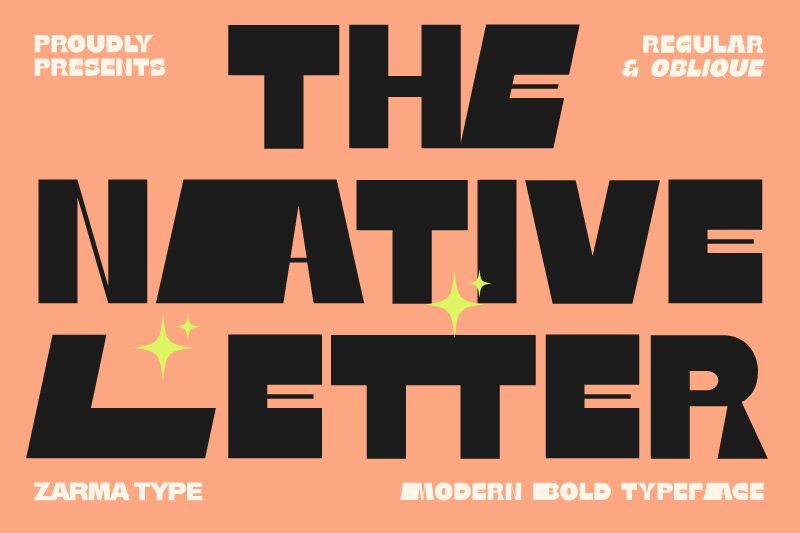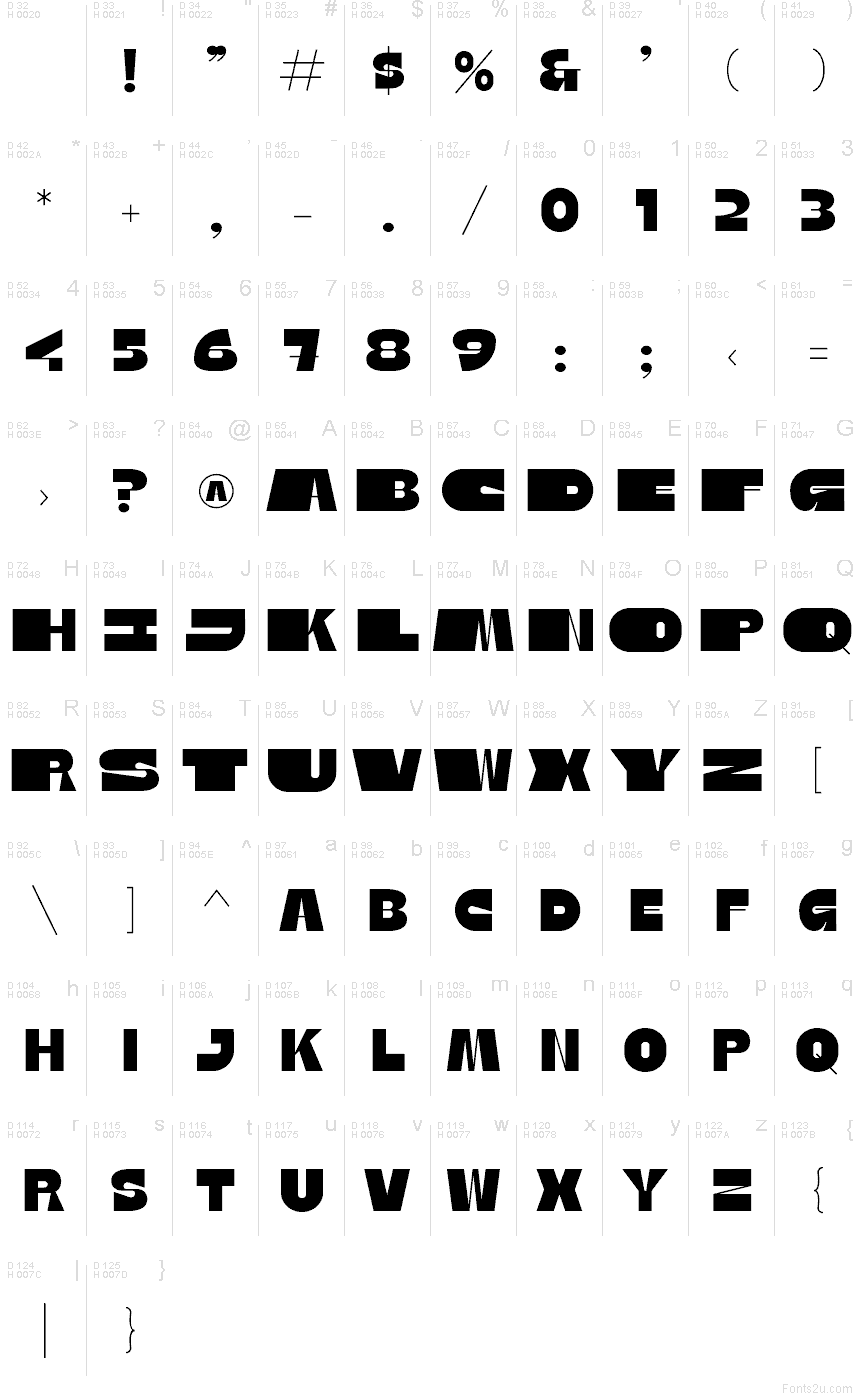
Native Letter od Zarma Type je bezplatné stencillové písmo v kmenovém stylu. Díky vysokým velkým písmenům a ostrým řezům působí znaky dojmem ručně vyřezávaného, až rituálního písma. Formy zůstávají výrazné a jednoduché, ale opakující se vnitřní zářezy a trojúhelníkové otvory dávají písmu kořeny v tradici malovaných nápisů, plakátové typografie a stylizovaného domorodého řemesla.
Hodí se pro obaly, plakáty na akce, hudební grafiku, branding restaurací a tématické titulky, kde je potřeba silný grafický prvek. Jako bezplatné písmo funguje dobře i pro krátké nadpisy, monogramy a obálky, protože vzorované řezy dodávají i běžným slovům vzhled razítka a osobitou tvář.